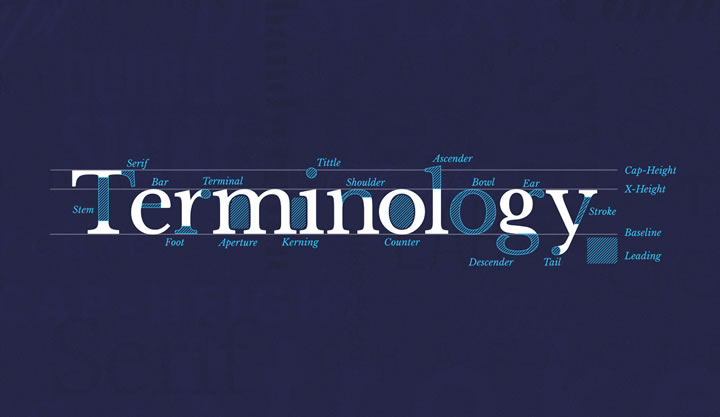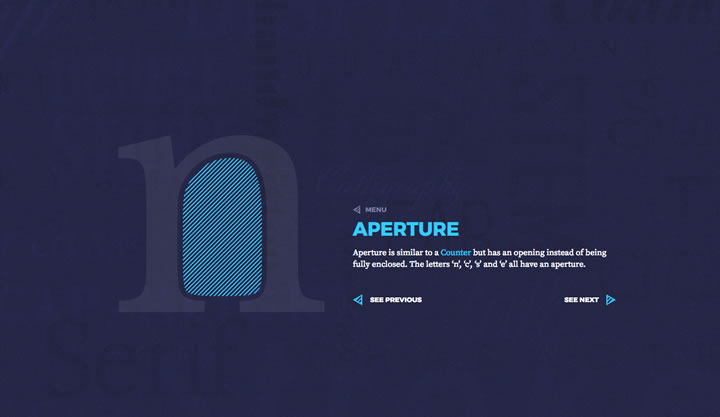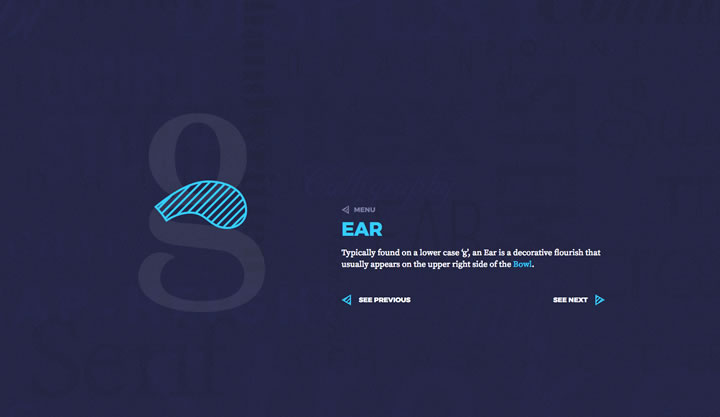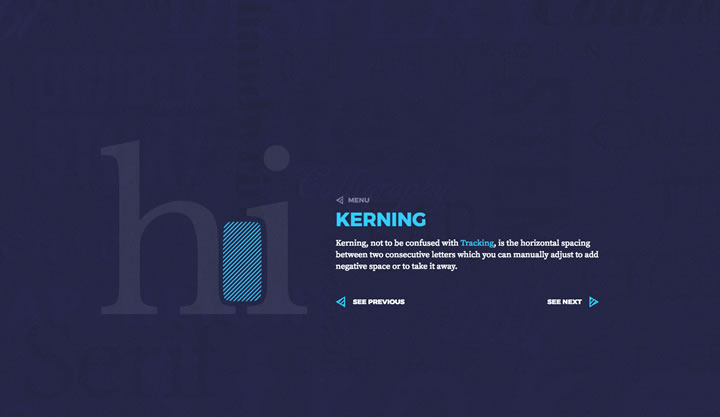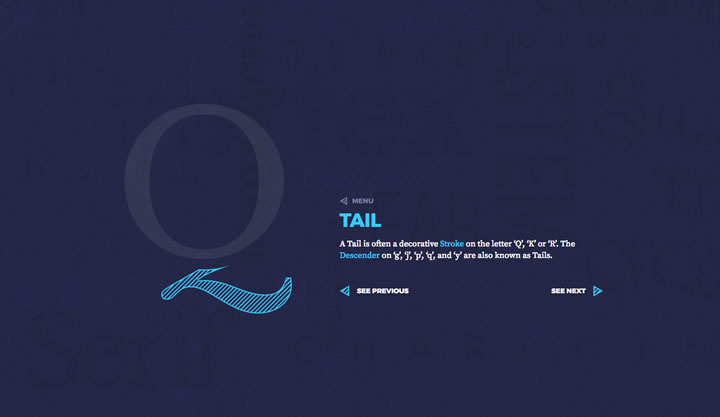
Comprendre les termes techniques de la typographie
Chaque typographie est différente et il en existe des milliers. Maintenant dans le monde de la typographie, il en existe certaines plus populaires que d’autres. Certaines par leur historique (Avangarde, DIN, Futura, Helvetica…) d’autres par leur innovation, côté frais, fun…
Dans tous les cas, il y a des mots à apprendre pour comprendre leur signification et donner l’intégration qu’elles mérites.
Voici rapidement quelques exemples de mots abordés :
- Stem : La tige, le corps principal de la lettre. Dans le même esprit que « Stroke »
- Serif : Elles sont les extensions rattachées à la tige. Cela à donné les Fonts « Serif » ou « à empattement ». A contrario les typos « sans-Serif »
- Bar : La partie horizontale qui traverse la lettre
- Eye : Espace enfermé dans une lettre.
- Foot : Partie basse d’une lettre qui apparait le plus souvent sur des fonts « Serif »
- Terminal : Représenté souvent par une boule (ou du genre) à la fin d’une lettre.
- Aperture : Les lettre « c », « n », « s » et « e » ont toujours une aperture. Un espace presque totalement fermé.
- Kerning : L’espace entre 2 lettres consécutives.
- Tittle : Le point sur les lettre « i » et « j »
- Shoulder : Partie arrondie d’une lettre faisant le lien entre la partie principale et l’extension. Se trouve sur les lettres « m », « n », « h ».